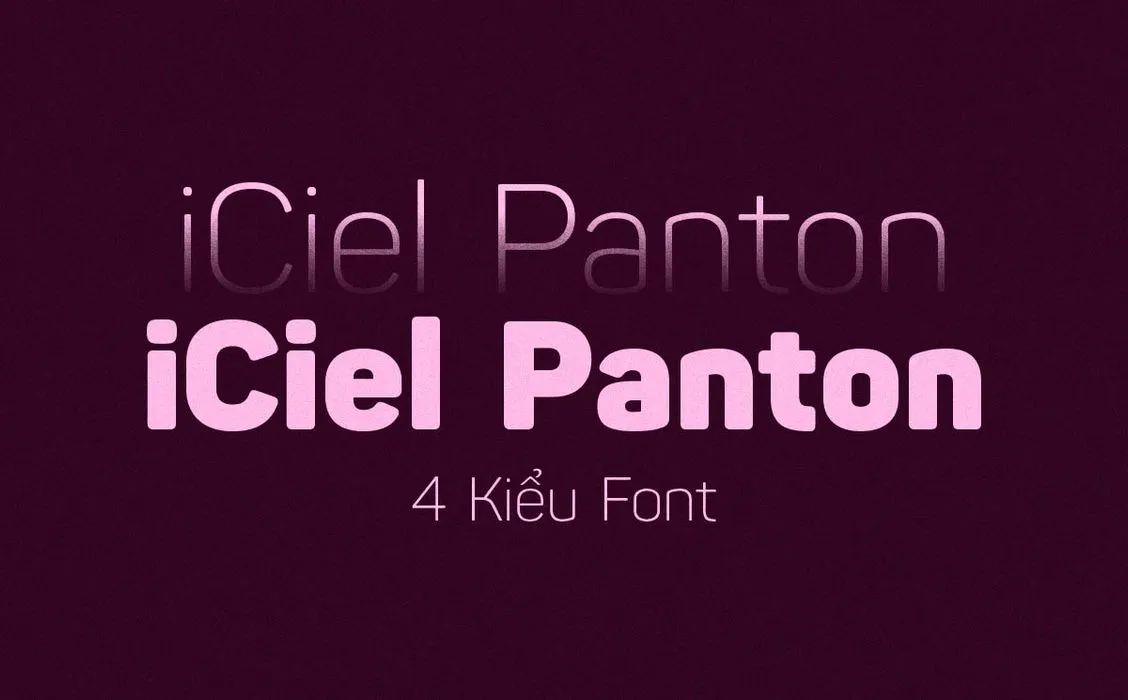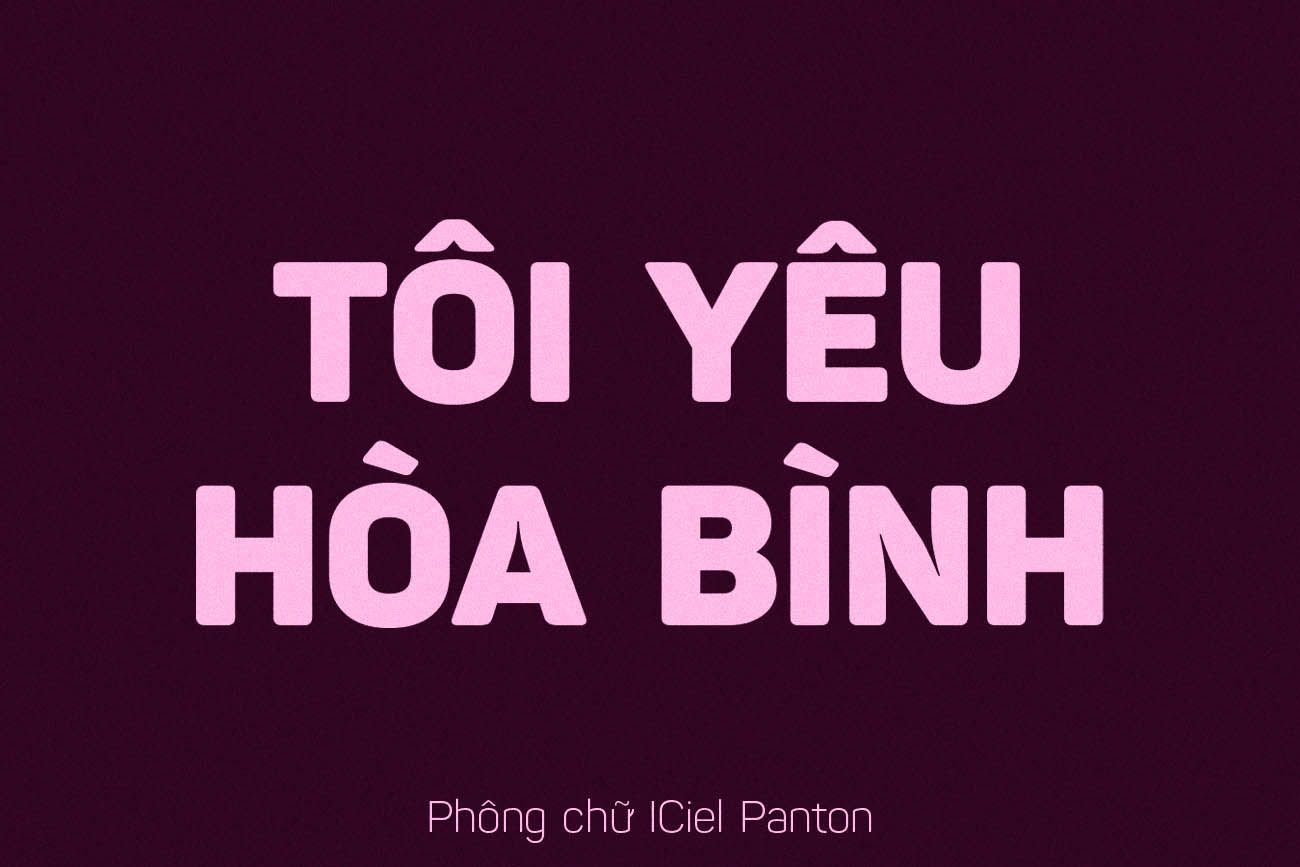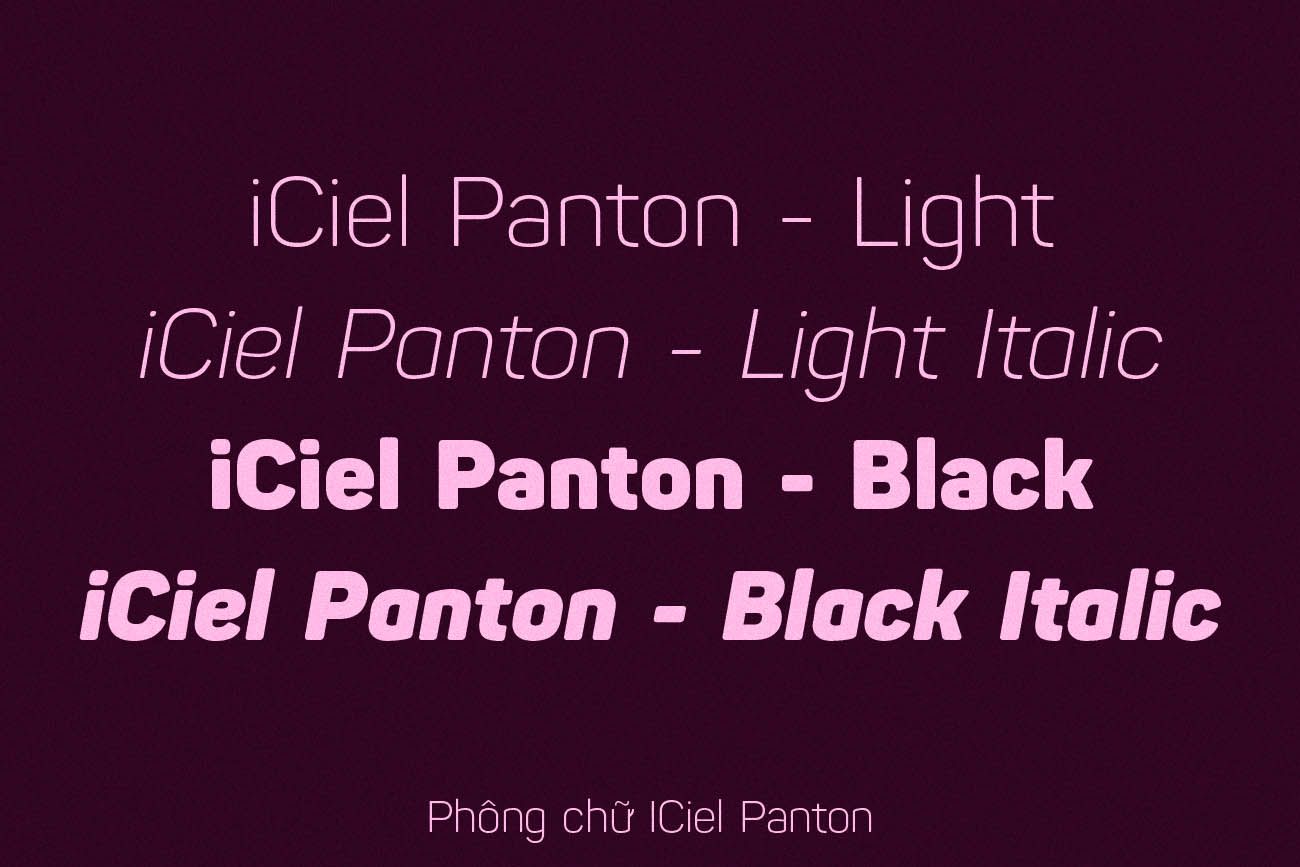
Trong thế giới thiết kế đồ họa, những bộ font sans-serif luôn giữ vị trí quan trọng nhờ sự rõ ràng, hiện đại và dễ ứng dụng. Trong số đó, font iCiel Panton là một lựa chọn nổi bật, vừa chuyên nghiệp vừa linh hoạt. Đây là phiên bản Việt hóa của bộ font Panton đình đám do Fontfabric phát triển, hiện đã trở thành công cụ quen thuộc với các nhà thiết kế tại Việt Nam.
Font gốc Panton được thiết kế bởi Fontfabric, một studio font quốc tế nổi tiếng với những bộ chữ sáng tạo, chuẩn mực và dễ dùng. Sau đó, iCiel Team đã Việt hóa trọn bộ, bổ sung đầy đủ hệ thống ký tự tiếng Việt mà vẫn giữ nguyên sự tinh tế trong từng đường nét. Nhờ vậy, font chữ iCiel Panton vừa đáp ứng nhu cầu thiết kế quốc tế, vừa phù hợp với thị trường Việt Nam.
iCiel Panton thuộc nhóm font chữ sans-serif mang phong cách geometric hiện đại. Các chữ cái có góc bo tròn nhẹ, tạo cảm giác thân thiện nhưng vẫn giữ sự mạnh mẽ và rõ ràng. Bộ font bao gồm nhiều biến thể từ Light, Regular đến Black, kết hợp cả italic, giúp nhà thiết kế dễ dàng sử dụng cho cả tiêu đề và văn bản dài.
Chính nhờ sự cân bằng giữa tính thẩm mỹ và tính ứng dụng, iCiel Panton thường được đánh giá cao trong các dự án cần sự chuyên nghiệp và dễ đọc.
Với sự đa dạng về trọng lượng và phong cách, font iCiel Panton có thể sử dụng trong nhiều loại dự án khác nhau:
Thiết kế logo và bộ nhận diện thương hiệu.
Poster quảng cáo, banner sự kiện, typography ấn tượng.
Giao diện website, app mobile, hoặc slide thuyết trình chuyên nghiệp.
In ấn catalogue, brochure, tạp chí, sách báo.
Nếu bạn đang tìm kiếm một font chữ sans-serif Việt hóa vừa hiện đại vừa dễ ứng dụng, font iCiel Panton chắc chắn là lựa chọn không thể bỏ qua. Sự kết hợp giữa thiết kế gốc từ Fontfabric và phiên bản Việt hóa chỉn chu từ iCiel Team giúp bộ font này trở thành công cụ mạnh mẽ cho cả thiết kế sáng tạo lẫn thương mại.